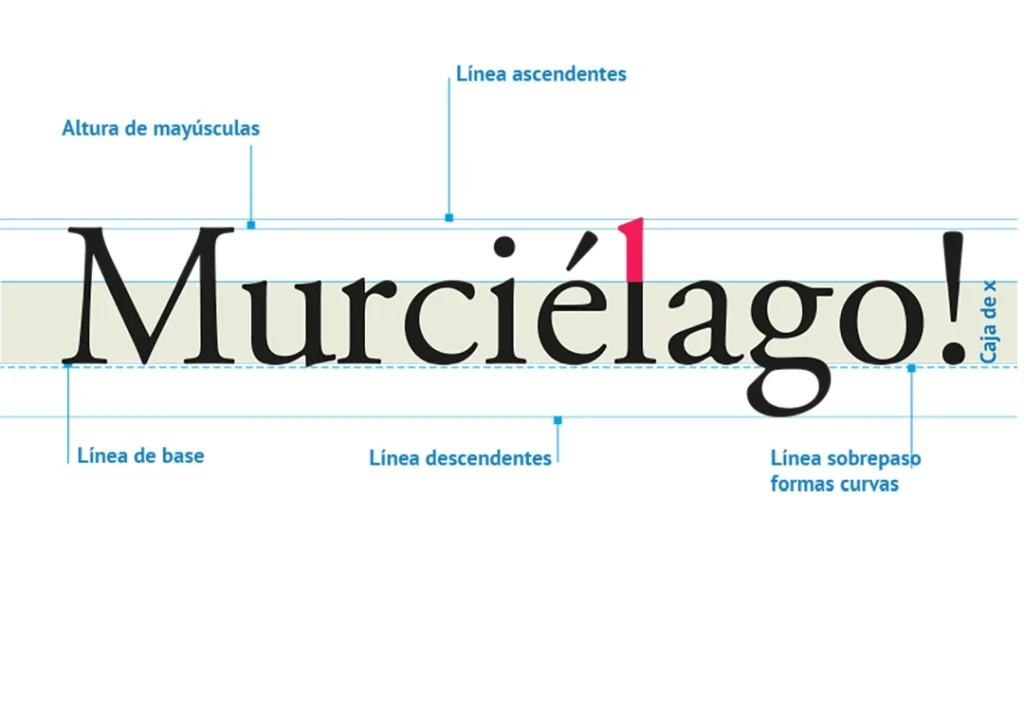
Dentro de la anatomía de los signos tipográficos en minúscula, se denomina ascendente a aquellos elementos que crucen el nivel superior de la caja de x.
En la imagen de ejemplo, la altura de las ascendentes es mayor que la altura de las mayúsculas.